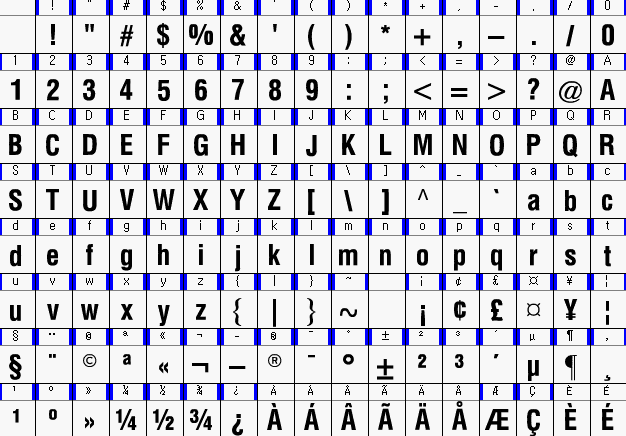
zBar-0
zBar-* series fonts are based on Zebra barcode label printer. The font format is TTF, which is convenient for users to print various labels.
Contoh hasil cetak:
Semua karakter font zBar-0:
Font zBar-0 dilihat dengan penampil font bawaan Windows: